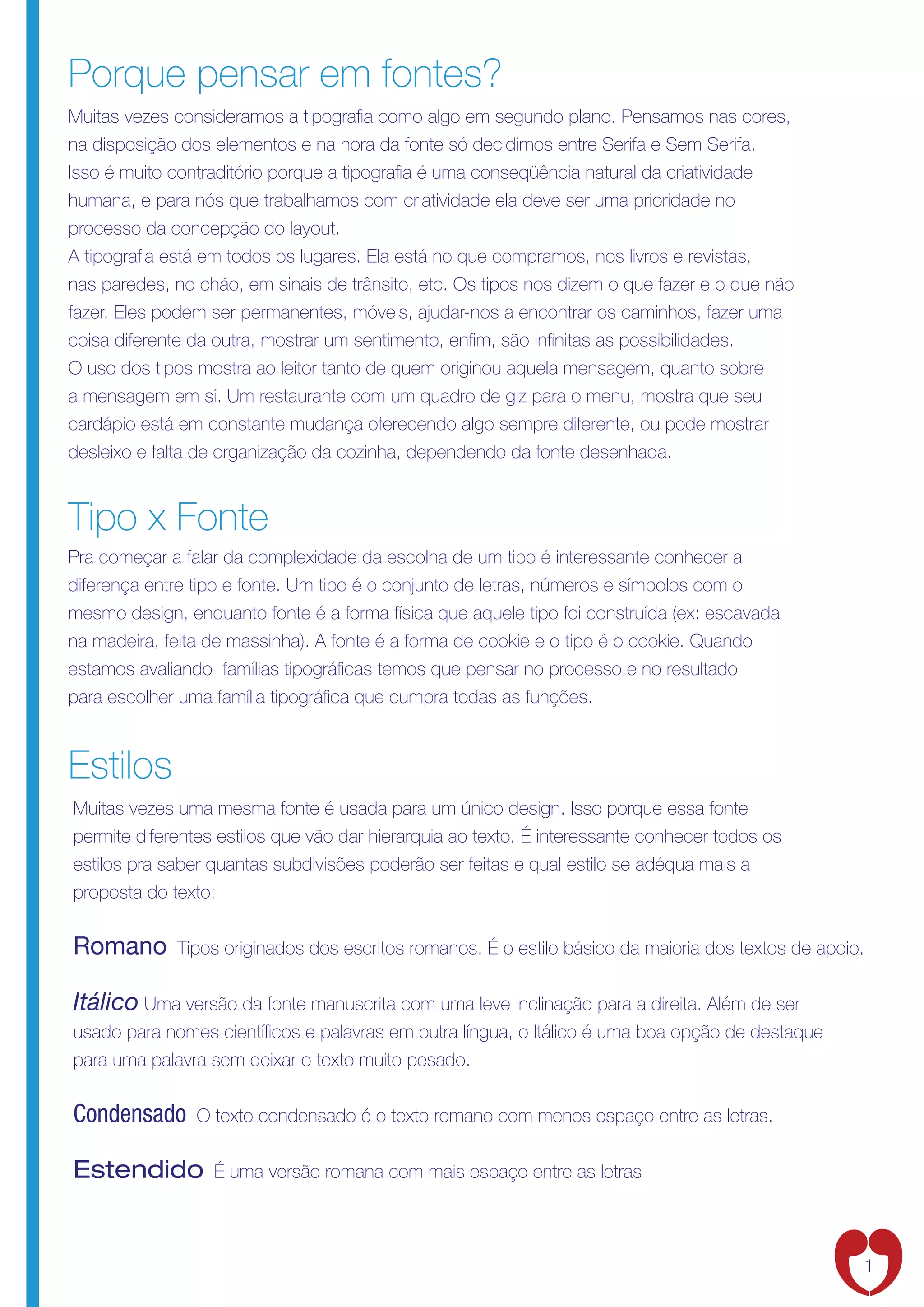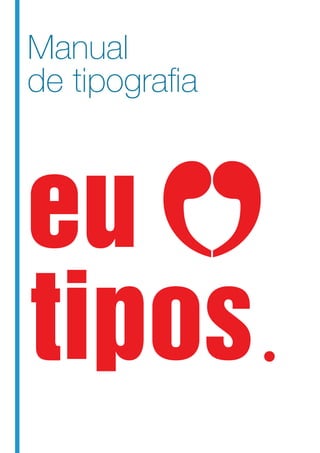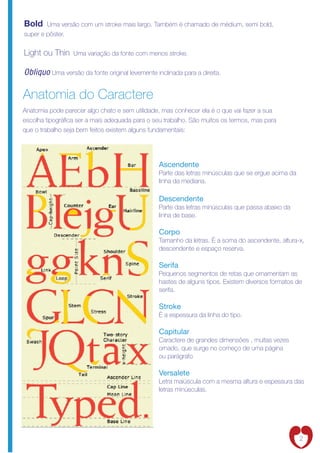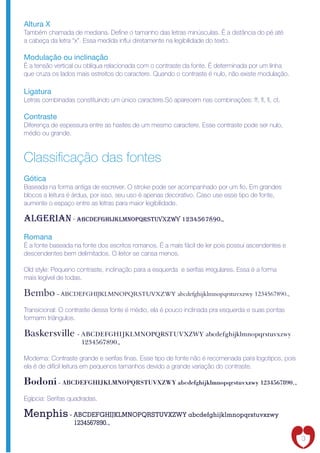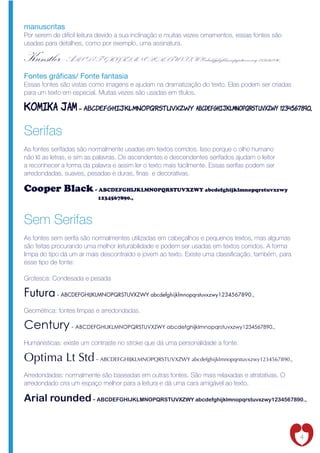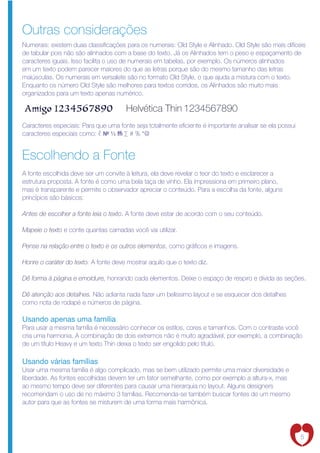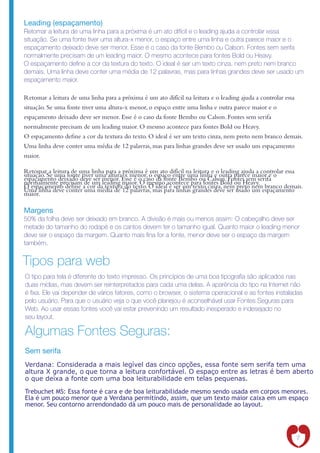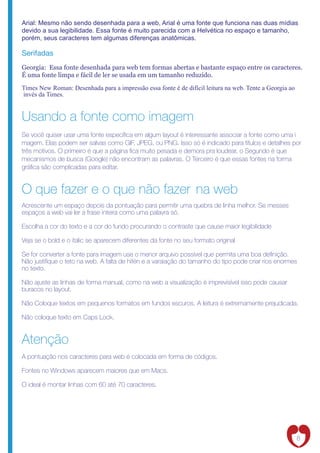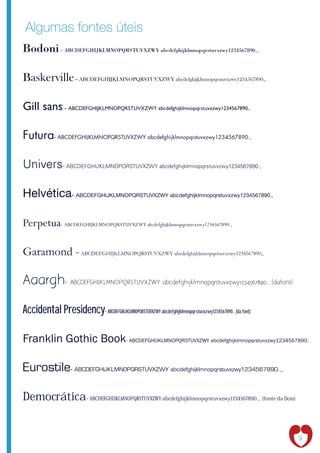
Porque pensar em fontes?
Muitas vezes consideramos a tipogra a como algo em segundo plano. Pensamos nas cores,
na disposição dos elementos e na hora da fonte só decidimos entre Serifa e Sem Serifa.
Isso é muito contraditório porque a tipogra a é uma conseqüência natural da criatividade
humana, e para nós que trabalhamos com criatividade ela deve ser uma prioridade no
processo da concepção do layout.
A tipogra a está em todos os lugares. Ela está no que compramos, nos livros e revistas,
nas paredes, no chão, em sinais de trânsito, etc. Os tipos nos dizem o que fazer e o que não
fazer. Eles podem ser permanentes, móveis, ajudar-nos a encontrar os caminhos, fazer uma
coisa diferente da outra, mostrar um sentimento, en m, são in nitas as possibilidades.
O uso dos tipos mostra ao leitor tanto de quem originou aquela mensagem, quanto sobre
a mensagem em sí. Um restaurante com um quadro de giz para o menu, mostra que seu
cardápio está em constante mudança oferecendo algo sempre diferente, ou pode mostrar
desleixo e falta de organização da cozinha, dependendo da fonte desenhada.
Tipo x Fonte
Pra começar a falar da complexidade da escolha de um tipo é interessante conhecer a
diferença entre tipo e fonte. Um tipo é o conjunto de letras, números e símbolos com o
mesmo design, enquanto fonte é a forma física que aquele tipo foi construída (ex: escavada
na madeira, feita de massinha). A fonte é a forma de cookie e o tipo é o cookie. Quando
estamos avaliando famílias tipográ cas temos que pensar no processo e no resultado
para escolher uma família tipográ ca que cumpra todas as funções.
Estilos
Muitas vezes uma mesma fonte é usada para um único design. Isso porque essa fonte
permite diferentes estilos que vão dar hierarquia ao texto. É interessante conhecer todos os
estilos pra saber quantas subdivisões poderão ser feitas e qual estilo se adéqua mais a
proposta do texto:
Romano       Tipos originados dos escritos romanos. É o estilo básico da maioria dos textos de apoio.
Itálico Uma versão da fonte manuscrita com uma leve inclinação para a direita. Além de ser
usado para nomes cientí cos e palavras em outra língua, o Itálico é uma boa opção de destaque
para uma palavra sem deixar o texto muito pesado.
Condensado      O texto condensado é o texto romano com menos espaço entre as letras.
Estendido         É uma versão romana com mais espaço entre as letras
Bold    Uma versão com um stroke mais largo. Também é chamado de médium, semi bold,
super e pôster.
Light ou Thin     Uma variação da fonte com menos stroke.
Obliquo Uma versão da fonte original levemente inclinada para a direita.
Anatomia do Caractere
Anatomia pode parecer algo chato e sem utilidade, mas conhecer ela é o que vai fazer a sua
escolha tipográ ca ser a mais adequada para o seu trabalho. São muitos os termos, mas para
que o trabalho seja bem feitos existem alguns fundamentais:
Ascendente
Parte das letras minúsculas que se ergue acima da
linha da mediana.
Descendente
Parte das letras minúsculas que passa abaixo da
linha de base.
Corpo
Tamanho da letras. É a soma do ascendente, altura-x,
descendente e espaço reserva.
Serifa
Pequenos segmentos de retas que ornamentam as
hastes de alguns tipos. Existem diversos formatos de
serifa.
Stroke
É a espessura da linha do tipo.
Capitular
Caractere de grandes dimensões , muitas vezes
ornado, que surge no começo de uma página
ou parágrafo
Versalete
Letra maiúscula com a mesma altura e espessura das
letras minúsculas.
Altura X
Também chamada de mediana. De ne o tamanho das letras minúsculas. É a distância do pé até
a cabeça da letra “x”. Essa medida in ui diretamente na legibilidade do texto.
Modulação ou inclinação
É a tensão vertical ou oblíqua relacionada com o contraste da fonte. É determinada por um linha
que cruza os lados mais estreitos do caractere. Quando o contraste é nulo, não existe modulação.
Ligatura
Letras combinadas constituindo um único caractere.Só aparecem nas combinações: ff, , , ct.
Contraste
Diferença de espessura entre as hastes de um mesmo caractere. Esse contraste pode ser nulo,
médio ou grande.
Classi cação das fontes
Gótica
Baseada na forma antiga de escrever. O stroke pode ser acompanhado por um o. Em grandes
blocos a leitura é árdua, por isso, seu uso é apenas decorativo. Caso use esse tipo de fonte,
aumente o espaço entre as letras para maior legibilidade.
algerian - abcdefghijklmnopqrstuvxzwy 1234567890.,
Romana
É a fonte baseada na fonte dos escritos romanos. É a mais fácil de ler pois possui ascendentes e
descendentes bem delimitados. O leitor se cansa menos.
Old style: Pequeno contraste, inclinação para a esquerda e serifas irregulares. Essa é a forma
mais legível de todas.
Algumas fontes úteis Bodoni- ABCDEFGHIJKLMNOPQRSTUVXZWY abcdefghijklmnopqrstuvxzwy1234567890., Baskerville - ABCDEFGHIJKLMNOPQRSTUVXZWY abcdefghijklmnopqrstuvxzwy1234567890., Gill sans - ABCDEFGHIJKLMNOPQRSTUVXZWY abcdefghijklmnopqrstuvxzwy1234567890., Futura- ABCDEFGHIJKLMNOPQRSTUVXZWY abcdefghijklmnopqrstuvxzwy1234567890., Univers- ABCDEFGHIJKLMNOPQRSTUVXZWY abcdefghijklmnopqrstuvxzwy1234567890., Helvética- ABCDEFGHIJKLMNOPQRSTUVXZWY abcdefghijklmnopqrstuvxzwy1234567890., Perpetua- ABCDEFGHIJKLMNOPQRSTUVXZWY abcdefghijklmnopqrstuvxzwy1234567890., Garamond - ABCDEFGHIJKLMNOPQRSTUVXZWY abcdefghijklmnopqrstuvxzwy1234567890., Aaargh- ABCDEFGHIJKLMNOPQRSTUVXZWY abcdefghijklmnopqrstuvxzwy1234567890., (dafont) Accidental Presidency- ABCDEFGHIJKLMNOPQRSTUVXZWY abcdefghijklmnopqrstuvxzwy1234567890., (da font) Franklin Gothic Book- ABCDEFGHIJKLMNOPQRSTUVXZWY abcdefghijklmnopqrstuvxzwy1234567890. Eurostile- ABCDEFGHIJKLMNOPQRSTUVXZWY abcdefghijklmnopqrstuvxzwy1234567890.,, Democrática- ABCDEFGHIJKLMNOPQRSTUVXZWY abcdefghijklmnopqrstuvxzwy1234567890.,, (fonte da Dois) 9